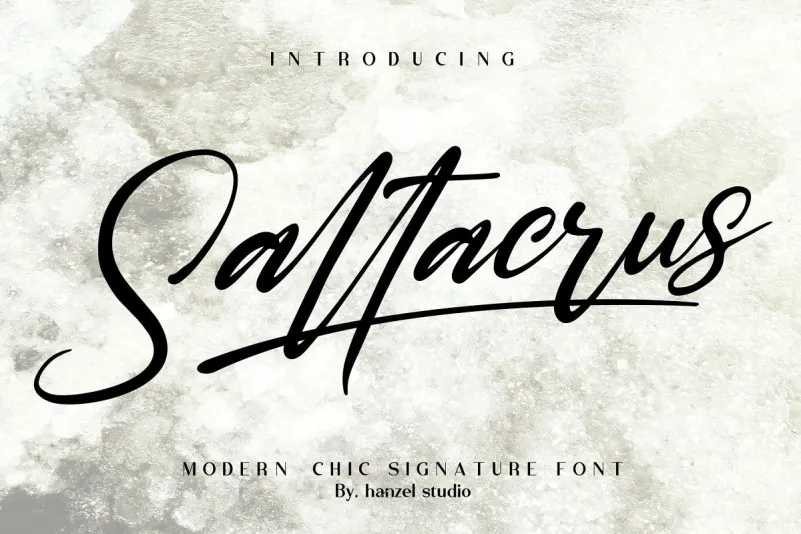
Saltacrus Script Font – Download Grátis
Esta é uma elegante fonte script moderna que combina a elegância de uma fonte clássica com o aspecto moderno. Ideal para nomes de títulos, esta fonte pertence ao catálogo de Saltacrus Font. Ela foi criada pelo Hanzel Studio e traz à tona uma tipografia chic e inovadora, repleta de realismo no estilo da escrita manual. A fonte é especialmente adequada para criação de logotipos, marcações digitais ou invitações casamentares, além de labels e revistas. Ademais, inclui um conjunto completo de letras manuscritas bonitas, números e uma ampla variedade de pontuação e ligaduras. Quer seja para assinaturas iniciais, logotipos pessoais ou como marca, a Saltacrus Font é perfeita para quem busca expressar-se com estilo e sofisticação em suas criações visuais. Sem dúvida, essa fonte atenderá todos os seus requisitos e muito além.